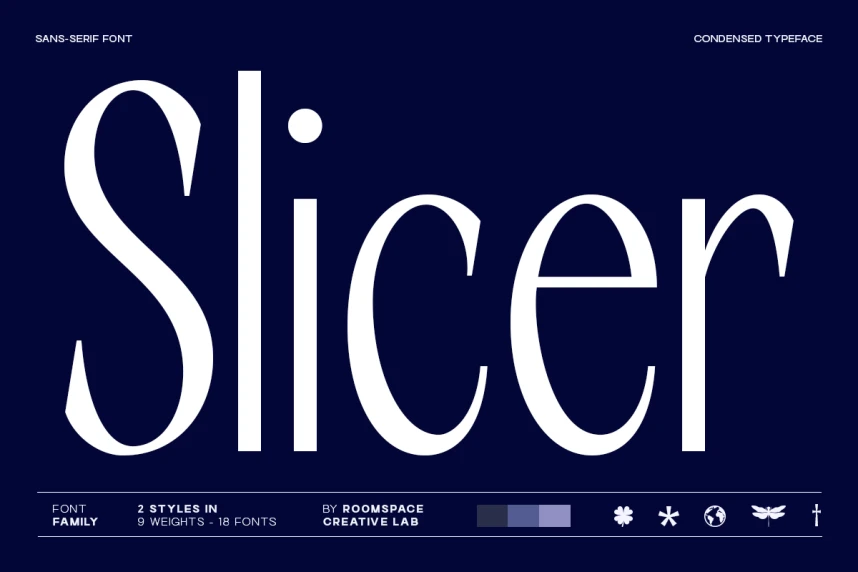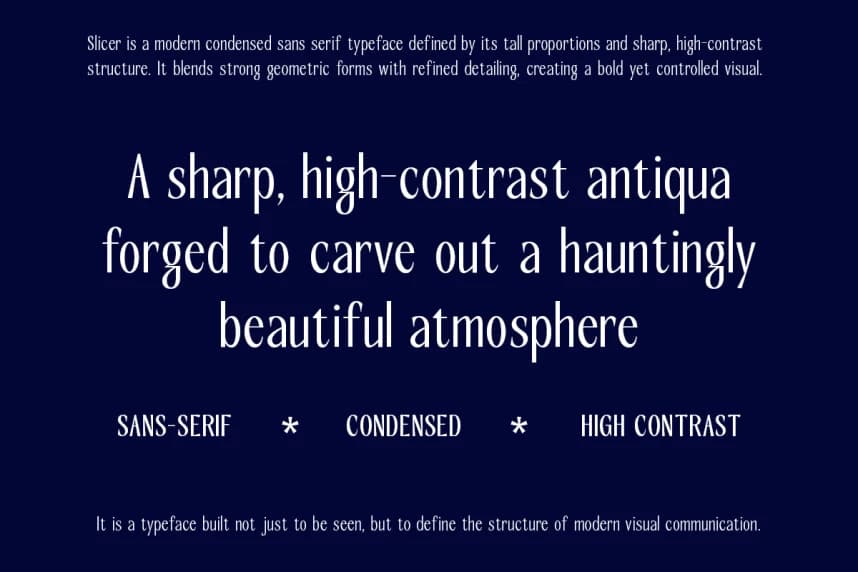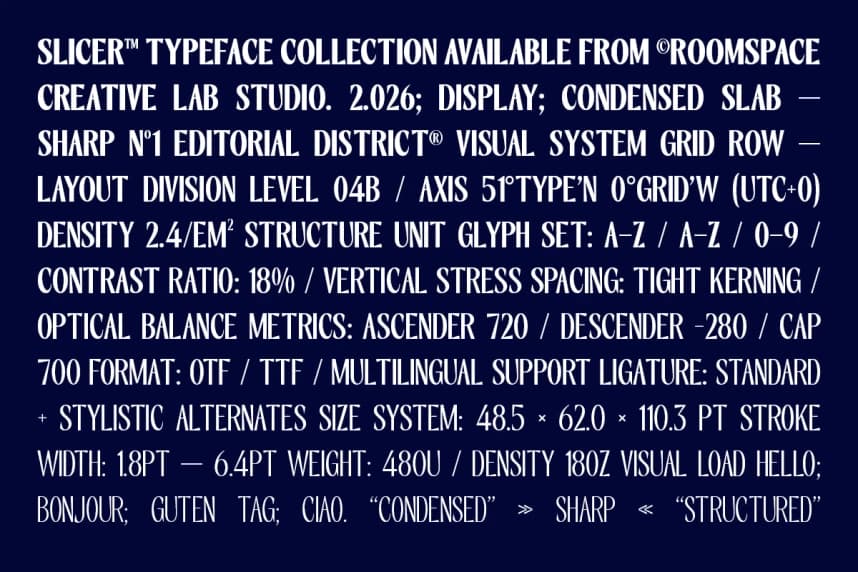
Slicer – Condensed Sans Serif Font Family
Slicer – Condensed Sans Serif Font Family, hassasiyet ve görsel etki arayan modern tasarımcılar için tasarlanmış sıkıştırılmış bir sans-serif font ailesidir. Dar oranlarıyla ve keskin kontrastıyla Slicer, temiz okunabilirliği sürdürürken güçlü bir görsel hiyerarşi yaratır.
Slicer – Condensed Sans Serif Font Family, hassasiyet ve görünürlük ihtiyacı duyan modern tasarımcılar için tasarlanmış daraltılmış bir sans-serif yazı tipi ailesidir. İnce oranları ve keskin kontrastı ile Slicer, temiz okunabilirliği korurken güçlü bir görsel hiyerarşi yaratır.